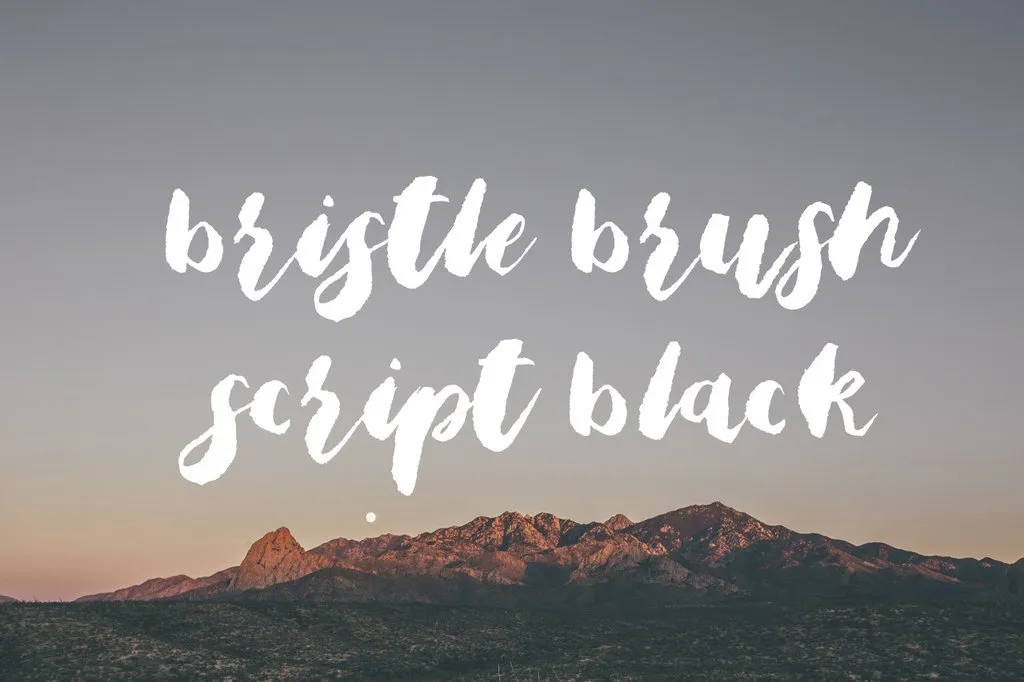
Bristle Brush Script Black Font
A Bristle Brush Script Black é uma adaptação cuidadosa do nosso tipo regular da Bristle Brush Script. Ela mantém a elegância e personalidade única do tipo, mas dá um tom mais sóbrio e definitivo ao estilo de escrita cursiva. As linhas são ainda mais grossas e delineadas, criando uma aparência que se assemelha mais à escrita da mão de um artista, sem o aspecto desbotado e suave do tipo regular. Essa fonte é perfeita para criar um visual elegante e atraente em qualquer projeto editorial ou design gráfico, seja ele para anúncios, editoriais ou elementos de marca. Com sua consistência firme e estilo de escrita única, a Bristle Brush Script Black oferece uma versão mais opressiva da mesma estética fluida que tanto adoramos. Se você busca um tipo regular com o aspecto robusto e realista de um lápis de tinta, essa é a fonte perfeita para você.